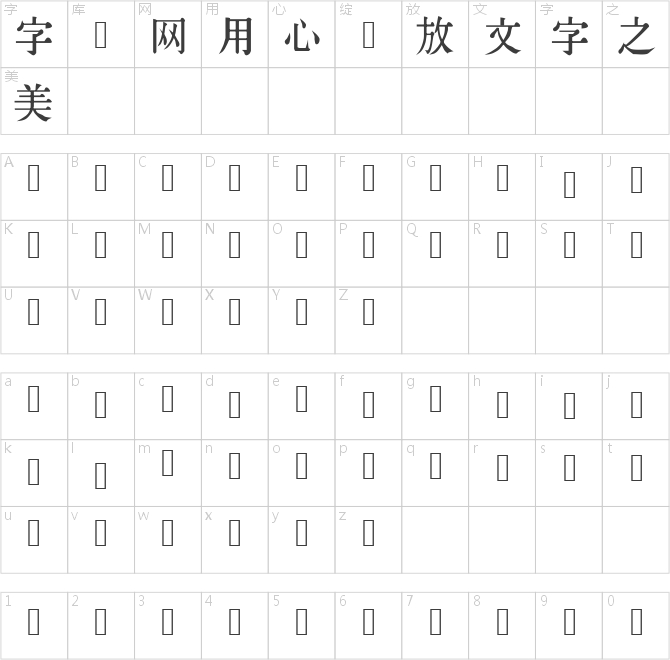
字體名稱: 同文新字典體
字體類型: 日文字體
作者版權: Yoshiki
同文新字典體
同文新字典體字體dejima-tsu3出島明朝フォント字庫是一款讓人賞心悅目、百看不厭的日文字體,適合各類廣告和產品包裝設計應用,字體大小4.36MB,格式為ttf字體,上傳用戶是welking,作者/版權方為Yoshiki Hayashi